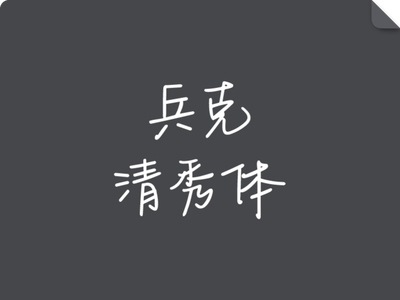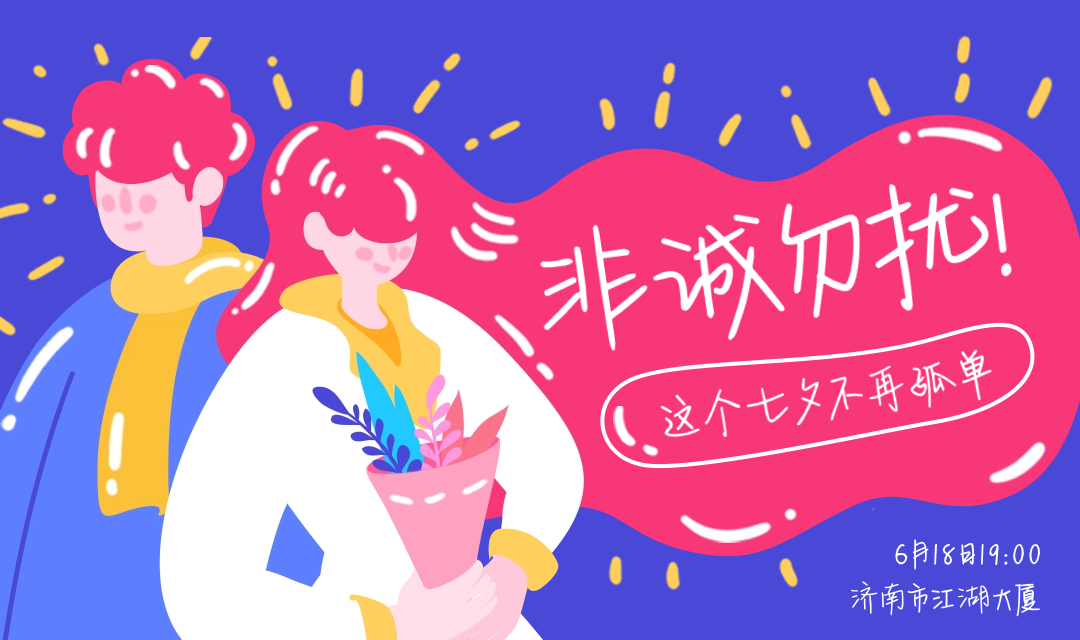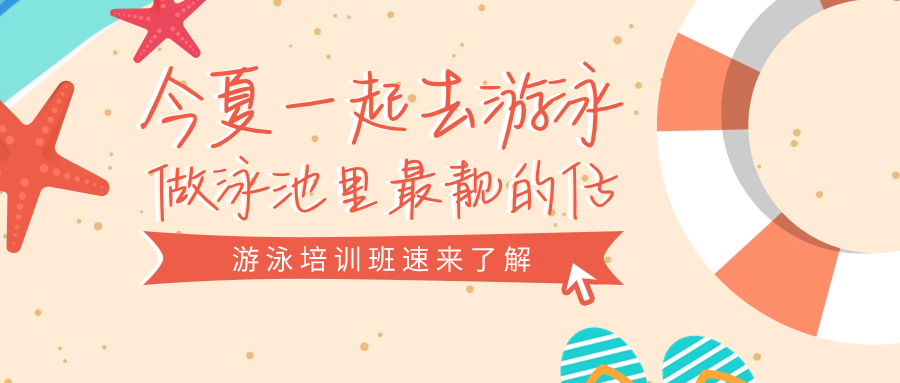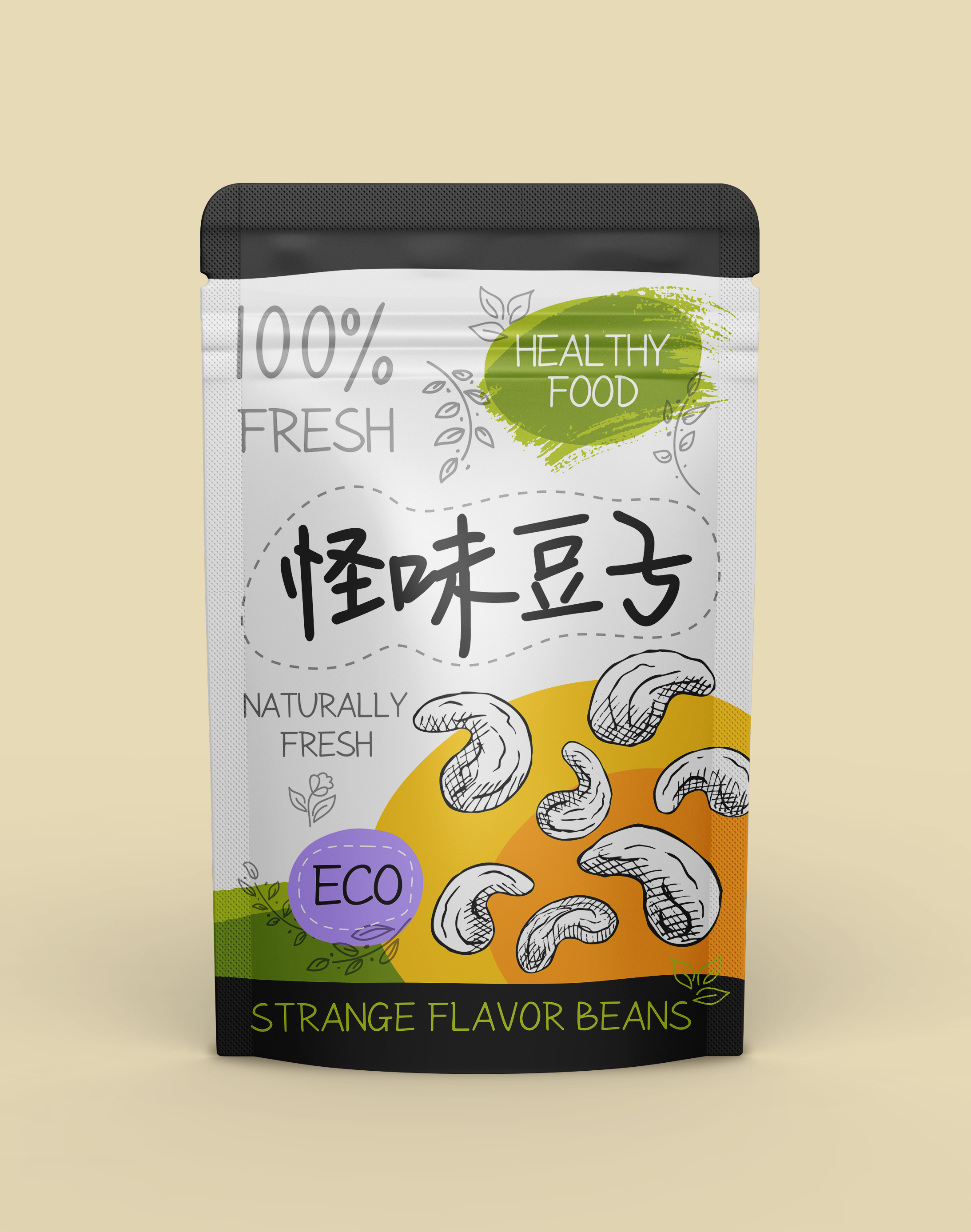
兵克清秀体
兵克清秀体,兵克清秀体,采用手写风格设计,每一笔每一划都透露出书写者的情感与温度。在创作过程中,对字体的笔画进行了巧妙的夸张处理,使得笔画在保持粗细相对统一的基础上,更加优美舒展,尤其是撇、捺、点等笔画,被刻意拉长,形成了一种独特的视觉美感,既增强了字体的动感,又赋予了其一种轻盈飘逸的气质,整体风格简约、潇洒、清爽,张弛且有序。适用于文学作品与诗集、品牌与包装设计、海报设计、广告宣传等视觉场景。字 体 ID:1468